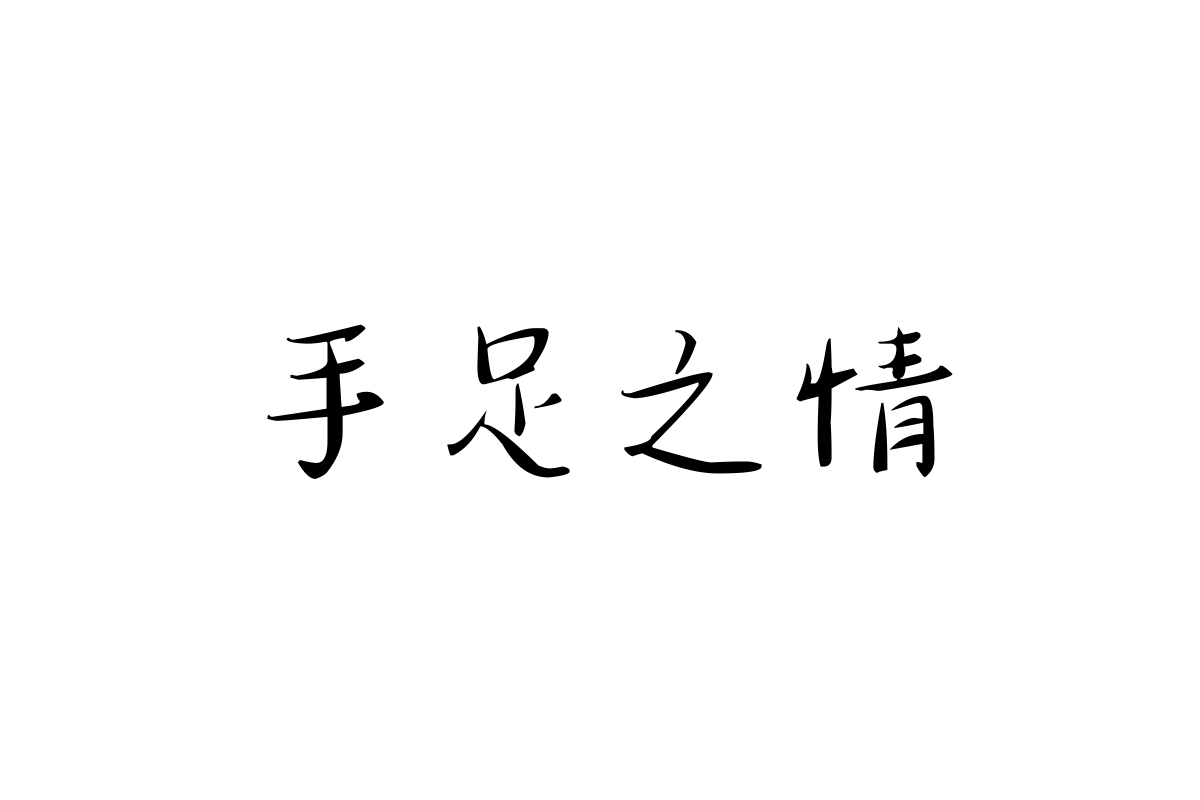
汉仪新蒂丝绸之路体是一款具有独特魅力的字体,它融合了东西方文化元素,展现出独特的韵味和风格。这款字体的特点如下:
1. 字形独特:汉仪新蒂丝绸之路体采用了独特的笔画结构和造型,使得每个字都呈现出独特的美感。这种独特的字形设计使得这款字体在视觉上具有很强的辨识度和吸引力。
2. 线条流畅:汉仪新蒂丝绸之路体的线条流畅自然,无论是横线、竖线还是曲线,都显得非常优美。这使得这款字体在书写过程中更加顺畅,提高了书写效率。
3. 结构严谨:汉仪新蒂丝绸之路体的字形结构严谨,每个字的笔画都经过精心安排,使得整个字体看起来更加和谐统一。这种严谨的结构使得这款字体在排版时更加规整,提高了整体效果。
4. 风格多样:汉仪新蒂丝绸之路体适用于各种场合,无论是用于书籍、杂志、海报、广告等,都能展现出其独特的魅力。此外,这款字体还支持多种字重和行距设置,满足不同需求。
总之,汉仪新蒂丝绸之路体是一款具有独特魅力的字体,无论是用于设计还是实际书写,都能展现出其独特的风采。
汉仪新蒂丝绸之路体